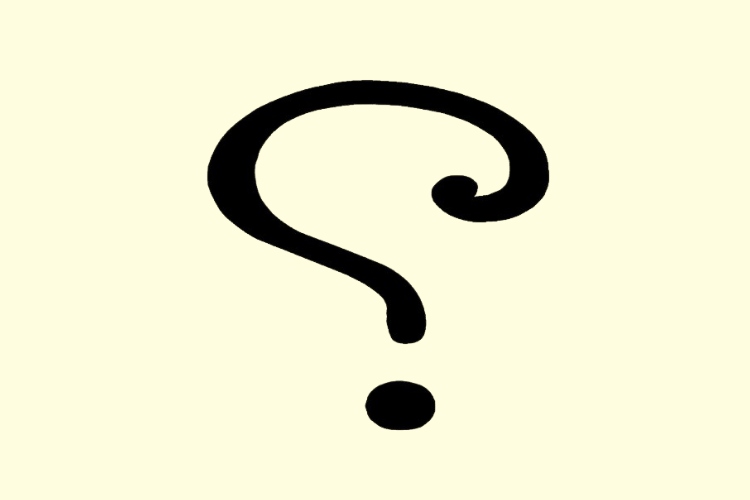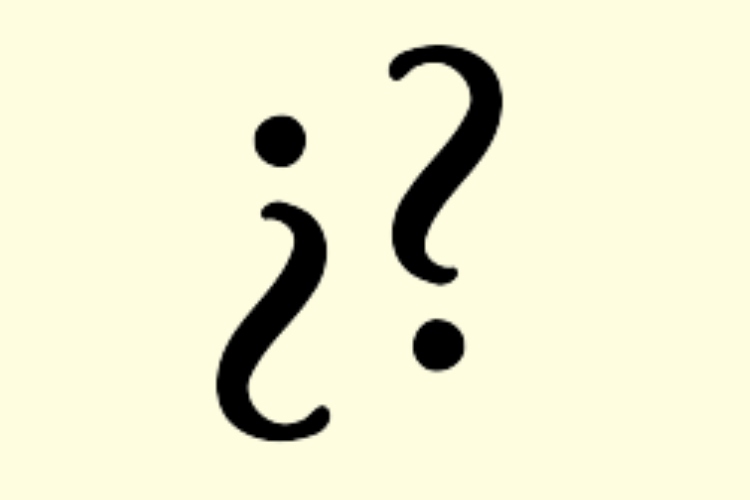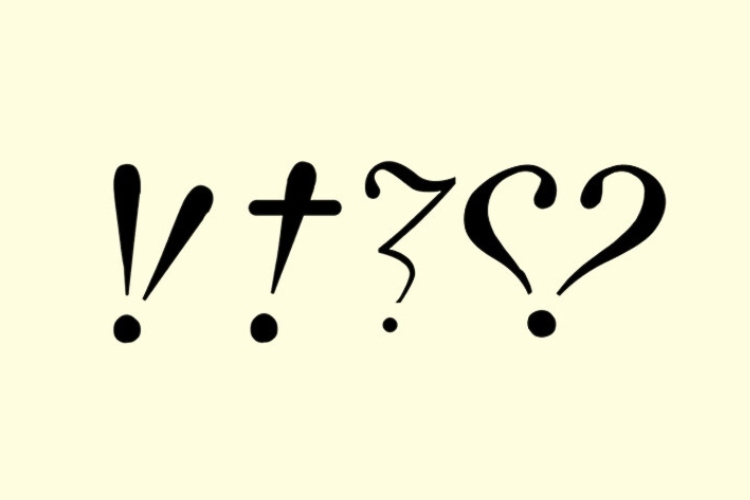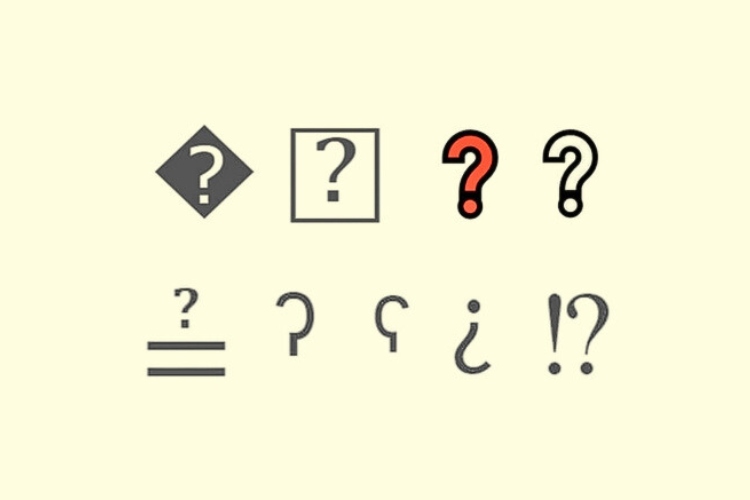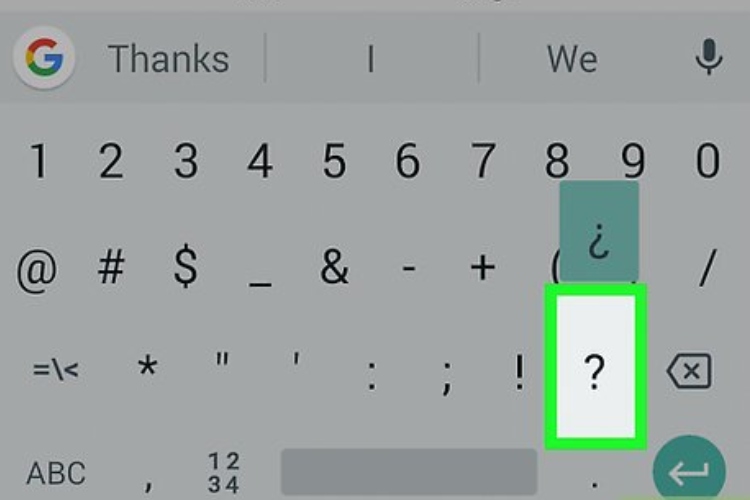
99+ dấu hỏi chấm ngược phổ biến, ấn tượng
99+ dấu hỏi chấm ngược phổ biến, ấn tượng gồm kiểu chữ sáng tạo và kiểu chữ ngẫu nhiên độc lạ dưới đây giúp bạn dễ dàng sao chép và sử dụng. Ngoài ra, Mobifonts còn cung cấp cho người đọc thông tin về ứng dụng phổ biến của dấu hỏi chấm ngược, hướng dẫn tạo và sử dụng dấu hỏi chấm ngược, đồng thời giải đáp một số câu hỏi phổ biến liên quan đến loại kí tự này.
Dấu hỏi chấm ngược (¿), còn gọi là dấu hỏi ngược hay chấm hỏi ngược, là một ký hiệu đặc biệt xuất hiện chủ yếu trong tiếng Tây Ban Nha. Ký tự này được đặt ở đầu câu hỏi và kết thúc bằng dấu hỏi chấm thông thường (?).
Dấu hỏi ngược có nguồn gốc từ quy tắc ngữ pháp Tây Ban Nha, được hoàng gia Tây Ban Nha chuẩn hóa từ thế kỷ 18. Mục đích của ký hiệu này là giúp người đọc nhận biết một câu hỏi ngay từ đầu, từ đó điều chỉnh ngữ điệu phù hợp khi đọc to hoặc giao tiếp.
Ngoài mục đích ngữ pháp truyền thống, dấu hỏi chấm ngược ngày nay được ứng dụng phổ biến như một dạng biểu tượng trang trí trong thiết kế nội dung, caption mạng xã hội hoặc đặt tên ký tự. Người dùng yêu thích sự sáng tạo thường xem chấm hỏi ngược là điểm nhấn đặc biệt trong bộ dấu chấm kí tự đặc biệt, góp phần làm cho nội dung trở nên sinh động, khác biệt và thu hút hơn.
Theo Unicode Consortium, phần lớn các dấu hỏi chấm nằm trong một số khối điển hình như: Basic Latin (U+0000–U+007F), Miscellaneous Technical (U+2300–U+23FF), Spacing Modifier Letters (U+02B0–U+02FF), Halfwidth and Fullwidth Forms (U+FF00–U+FFEF), Specials (U+FFF0–U+FFFF),... Dưới đây là các biến thể của dấu hỏi chấm chuẩn Unicode được dùng phổ biến:
Ngoài ra, một số tổ hợp biểu tượng như ¿?, ¿❓, ⬛❔ là sự kết hợp của nhiều ký tự Unicode và không có mã Unicode duy nhất.
Bộ sưu tập dưới đây sẽ gợi ý cho bạn những mẫu chữ dấu hỏi chấm ngược sáng tạo và cực kỳ thu hút theo nhiều phong cách khác nhau.
Bộ sưu tập những mẫu chữ dấu hỏi chấm ngược sáng tạo và kí tự ngẫu nhiên độc lạ dưới đây cho phép bạn tạo nên nhiều phong cách ấn tượng:
Những kiểu dấu hỏi chấm ngược sáng tạo dưới đây mang phong cách biến hóa đầy thú vị, từ dễ thương, gợi cảm đến độc lạ và cực kỳ “ngầu”:
Khi tên hiển thị cần điểm nhấn lạ mắt, kí tự ngẫu nhiên chính là lựa chọn cực chất. Dưới đây là một số kiểu chữ ngẫu nhiên độc lạ, mang phong cách riêng, giúp bạn tạo ấn tượng không trùng lặp.
Dấu hỏi chấm ngược không chỉ là biểu tượng trang trí mà còn là công cụ thể hiện phong cách cá nhân trong các nền tảng khác nhau. Thông tin dưới đây cung cấp cho bạn các ứng dụng phổ biến của dấu hỏi chấm ngược bao gồm: tên game, bình luận và tiểu sử cá nhân.
Dùng dấu hỏi ngược (¿) trong tên game là một cách tuyệt vời để tạo dấu ấn riêng.
Trong các tựa game như Free Fire, Liên Quân hay nhiều game mobile khác, hệ thống thường cho phép người chơi tự do cá nhân hóa tên nhân vật. Việc chèn ký tự đặc biệt như ¿, ¿Sniper?, ¿DarkBoy¿, hay các biến thể tương tự giúp tên game trở nên độc đáo, dễ nhận diện, và không bị trùng lặp với người chơi khác.
Dùng dấu hỏi chấm ngược như ¿ hoặc ¿? trong bình luận là một cách thông minh để tăng yếu tố hài hước, châm biếm hoặc khiến người đọc phải suy ngẫm. Ví dụ: “Bạn nghĩ mình đúng ¿” “Đây là kết thúc sao ¿?. Khác với dấu chấm hỏi thông thường, việc dùng ¿ giúp câu bình luận trở nên sắc sảo, khác biệt và dễ nổi bật hơn, đặc biệt là trên các nền tảng mạng xã hội (TikTok, Facebook, Instagram, Zalo, Threads).
Tiểu sử TikTok, Facebook hoặc Zalo rất cần sự khác biệt. Thêm chấm hỏi ngược vào câu mô tả trong tiểu sử cá nhân có thể giúp bạn tạo điểm nhấn và truyền tải thông điệp sáng tạo. Một số gợi ý bio có thể dùng như sau:
**¿**Em ổn không, em không biết nữa
**¿**Tôi là ai trong thế giới này
**¿**Đừng hiểu lầm, tôi cố tình đấy